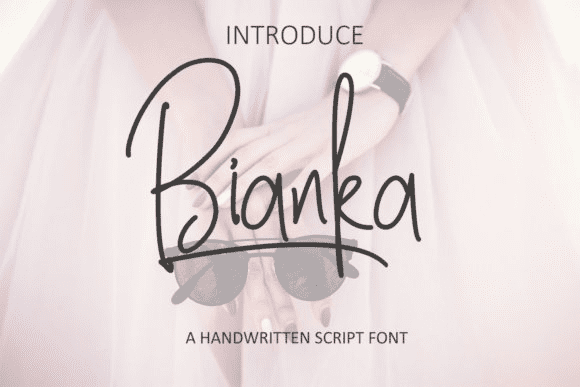
Название: Bianka Font (2021)
Bianka - это потрясающий монолитный шрифт, идеально подходящий для использования в моде и других стильных отраслях.
Этот простой, рукописный скорописный шрифт добавит тонны стиля и элегантности в ваши проекты.
Название: Bianka Font (2021)
Bianka - это потрясающий монолитный шрифт, идеально подходящий для использования в моде и других стильных отраслях.
Этот простой, рукописный скорописный шрифт добавит тонны стиля и элегантности в ваши проекты.